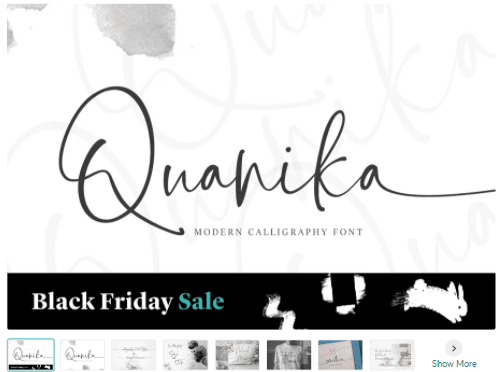
Quanika Font
Quanika - прекрасный и неподвластный времени рукописный шрифт. Это лучший выбор для создания привлекательных логотипов, брендов и цитат. Каждая буква имеет уникальный и красивый штрих, который оживит ваш дизайн! Этот шрифт имеет кодировку PUA, что означает, что вы можете легко получить доступ ко всем глифам и росчеркам!